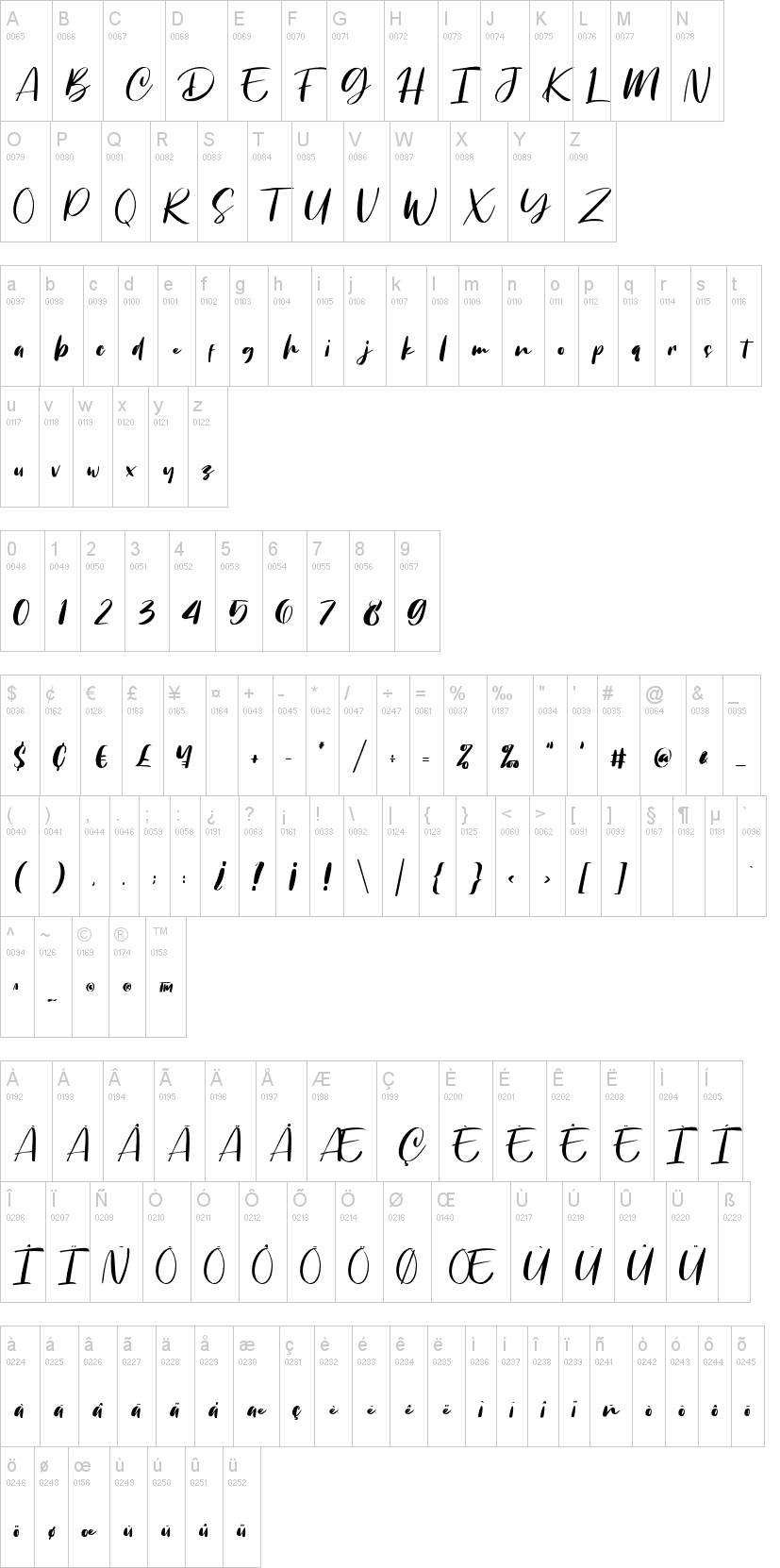
Chellyne
Chellyne 字体是一款精致的英文字体,它由著名的设计师Chellyne Powell设计。Chellyne字体拥有柔和的曲线,精细的细节,简约的风格,以及稳定的字体框架,可以提供更多的可读性。它可以用于任何类型的文档,特别适合用于报纸,杂志,书籍和网站的标题,副标题和正文。Chellyne字体还可以用于创建印刷品,如海报,名片,标签,标志和其他印刷品。
Chellyne是一款非常不错的手写艺术字体,具有很好的视觉感,适合于文化类的宣传设计、商业类品牌的广告和产品包装设计以及个性化文字排版等较多场景。
Chellyne字符映射图